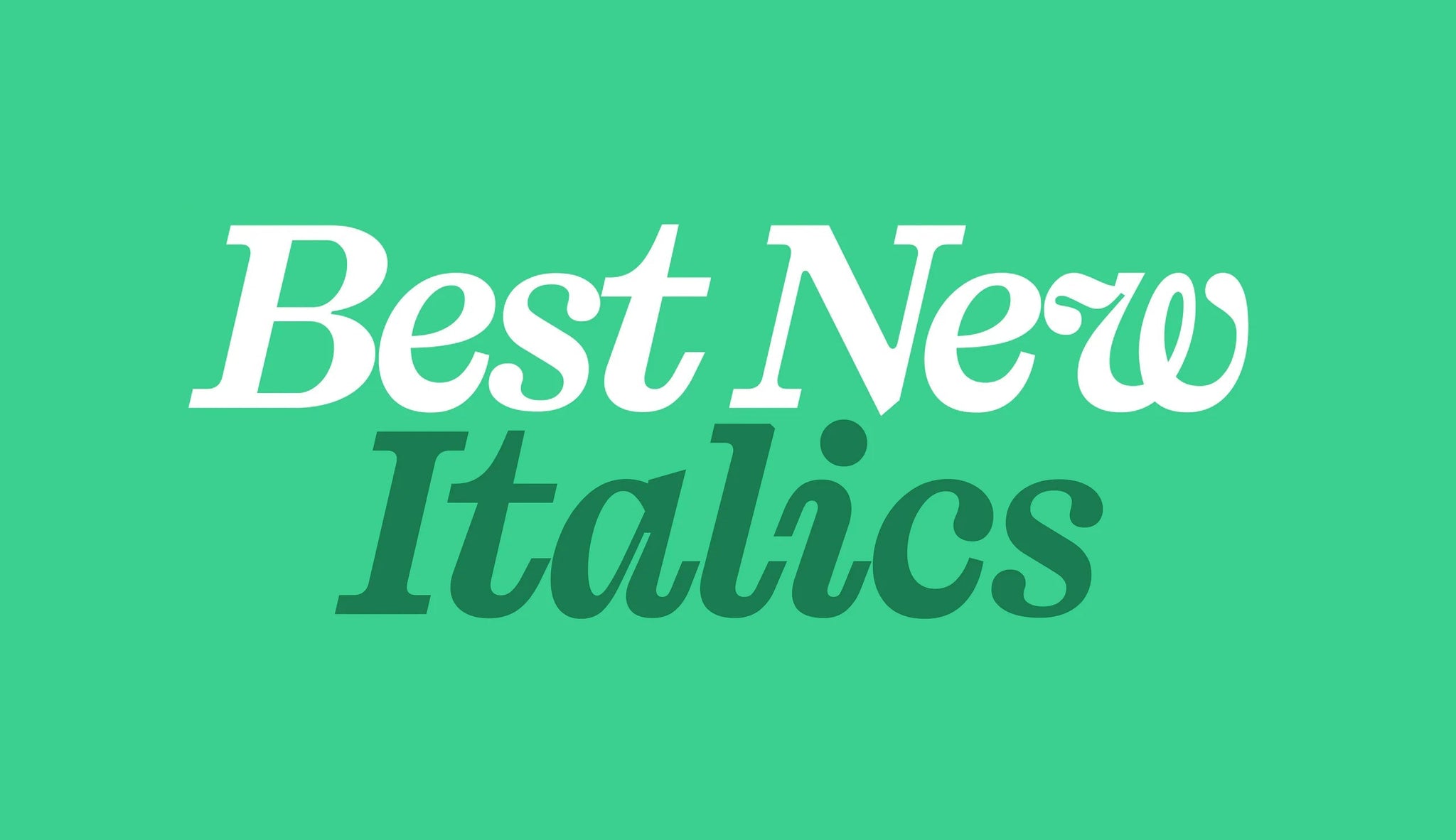
Les polices italique ont de nombreuses utilisations : ajouter du drame, du contraste, souligner un mot ou simplement pour l’esthétique. Mais ce qu’elles apportent vraiment, c’est un caractère défini à une famille de polices – insufflant personnalité, intention et mouvement face à des styles plus statiques et droits. Leur intégration offre l’opportunité d’explorer le caractère et l’art d’une police, ainsi que son contraste, quel que soit son usage prévu.
Dans ce tour d’horizon, nous mettons en lumière les styles italiques qui ont marqué 2025 – des sérifs classiques aux sans-serif les plus expressifs – chacun conçu avec intention et personnalité.
PP Editorial New
Une police classique dans une coupe classique. Les italiques de PP Editorial New sont parmi les plus distinctives de la bibliothèque Pangram Pangram. Conçues pour structurer les contenus éditoriaux longs, ces italiques offrent une fonction pragmatique tout en apportant une touche de style – une expressivité rappelant les magazines et publications mode des années 90. Élégance sans jamais paraître démodée.
PP Kyoto
Vous vous êtes déjà demandé si un slab serif pouvait être gracieux ? Les italiques de PP Kyoto en sont la réponse. Conçues dans le cadre d’un système bilingue Latin/Japonais, ces coupes italique reprennent le poids distinctif du slab tout en introduisant un rythme dynamique. Terminaisons en goutte, inclinaison expressive et contre-formes généreuses donnent un flux naturel, jamais forcé.
PP Acma
Avec des italiques fraîchement créées, le style incliné tant attendu de PP Acma est enfin là – et il valait chaque seconde d’attente. Là où les coupes droites oscillent entre subtilité et impact, les italiques s’engagent pleinement dans leur côté sensuel et expressif. Les courbes sont encore plus prononcées et la tension entre structure et liberté est plus palpable que jamais.
PP Nikkei
Les italiques de PP Nikkei, surtout dans les graisses plus lourdes, apportent chaleur, narration et dynamisme à une police déjà riche de résonances culturelles. Inspirées des histoires et traditions visuelles nippo-américaines, elles conservent la force des coupes droites tout en ajoutant une légèreté calligraphique qui les fait vibrer, pour un rythme et une sensation plus nuancés.
PP Right Gothic
Le sans moderne rencontre l’ADN historique dans PP Right Gothic Italic – un style phare parmi près de cent variantes. Là où beaucoup d’italiques gothiques ou grotesques semblent secondaires, les styles inclinés de Right Gothic sont réfléchis, contemporains et pleins de caractère. Le contraste marqué des traits (rare pour des italiques sans-serif) leur confère une énergie presque « serif ». De plus, tout est variable, vous permettant d’ajuster inclinaison, contraste et graisse à volonté !
PP Neue Montreal
PP Neue Montreal Italic est nette, précise et résolument moderne. En tant que grotesque, les italiques gardent la structure serrée et l’énergie élevée, assez subtiles pour le texte courant mais suffisamment dynamiques pour les titres. Les formes inclinées apportent un punch amical à un design sérieux, et les italiques légèrement resserrées offrent juste assez de distinction pour paraître intentionnelles et non par défaut.